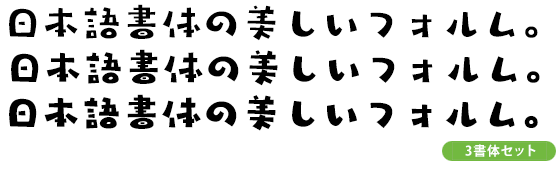
タカラクエン角 M
Takarakuen-kaku-M
手書き書体の「タカ楽円」のキレイバージョン。つまり「タカ楽円」の輪郭の多少の粗さをなくし、データを「キレイ」なものにしたもの。キレイバージョンでは書体名は漢字から「カタカナ」に変えて分かりやすくしている。手書き感を生かしながらエレメント、囲み等に「丸」を取り入れたデザインで可愛い書体。
タカ書体の紹介
モリサワ社のタカハンドでもおなじみのタイプ作家 高原新一氏が創作する個性豊かなデザインフォントブランド。どの書体も人間味に溢れ、温もりのある魅力的なフォントばかりです。一貫した創作テーマは「手書き風の味わいと温もり」。ファミリーを基本として制作し、多くのデザイナーに親しまれています。